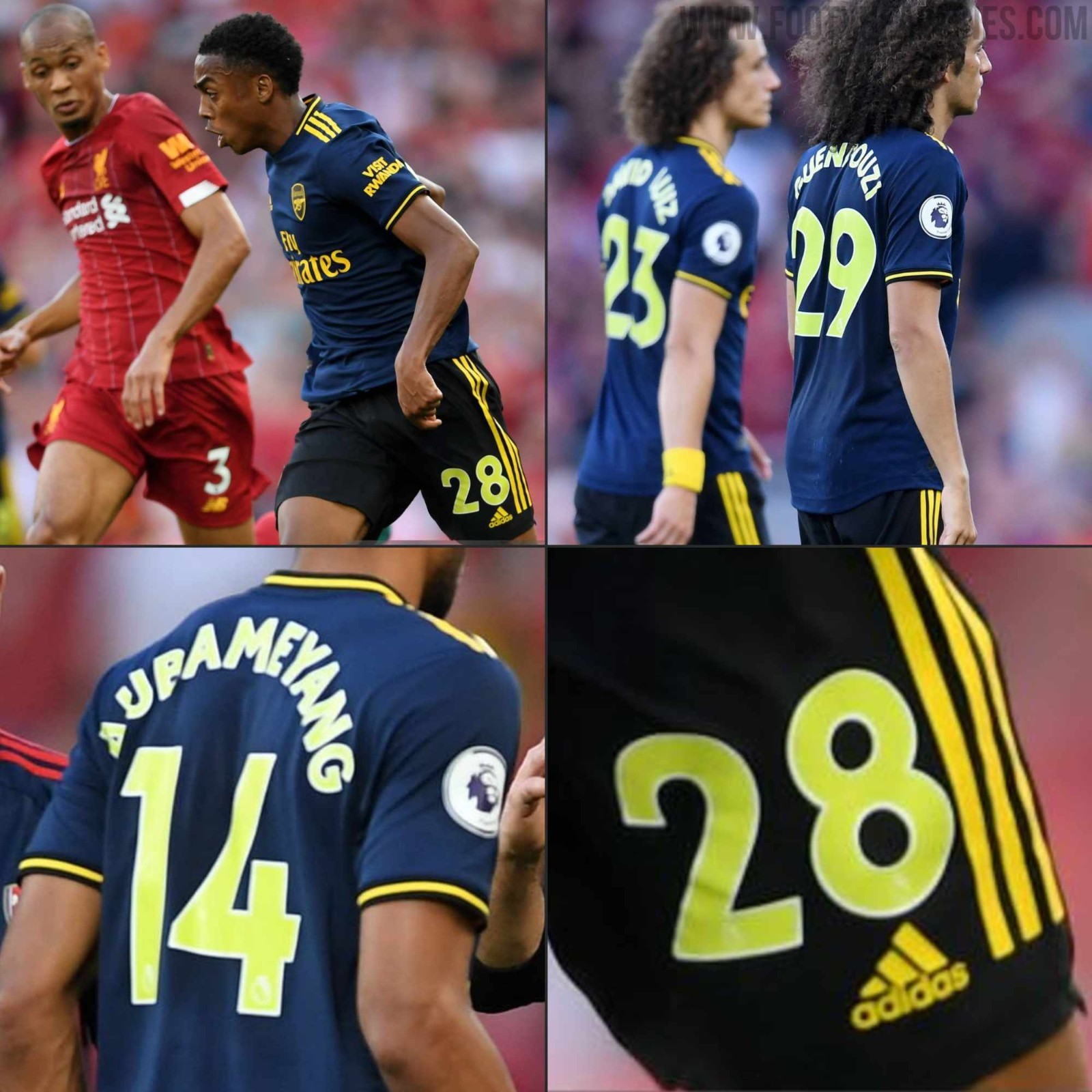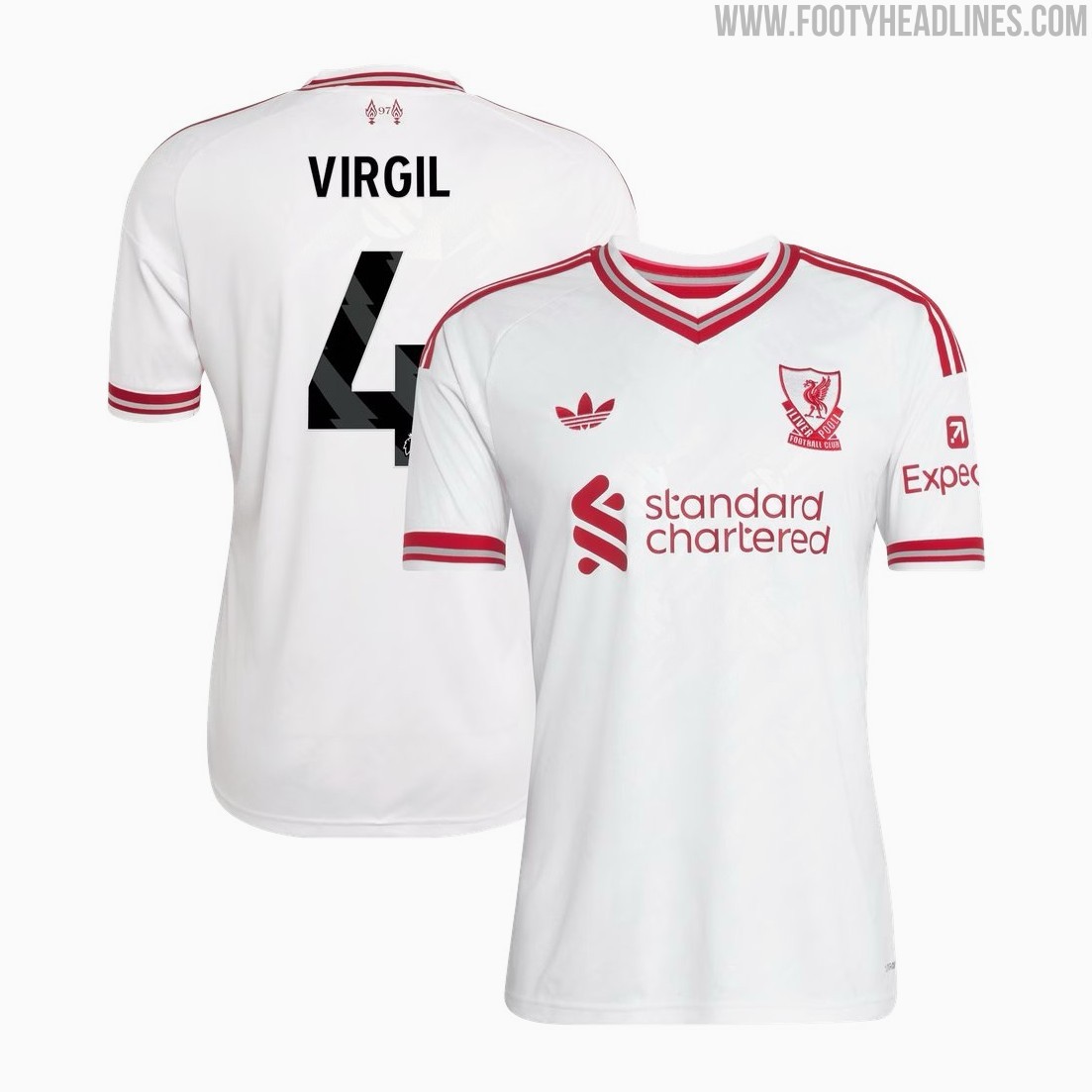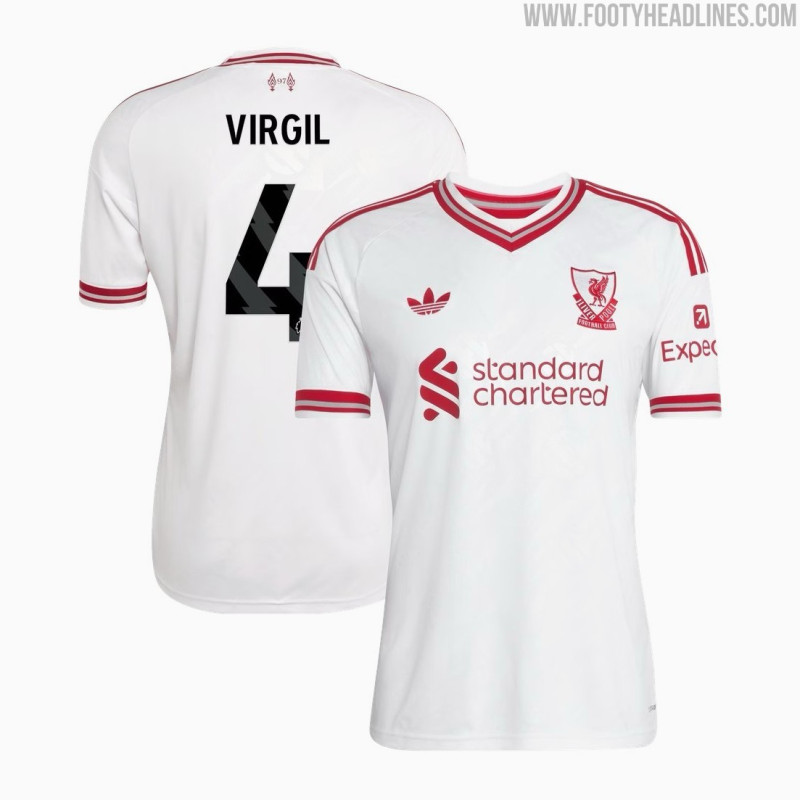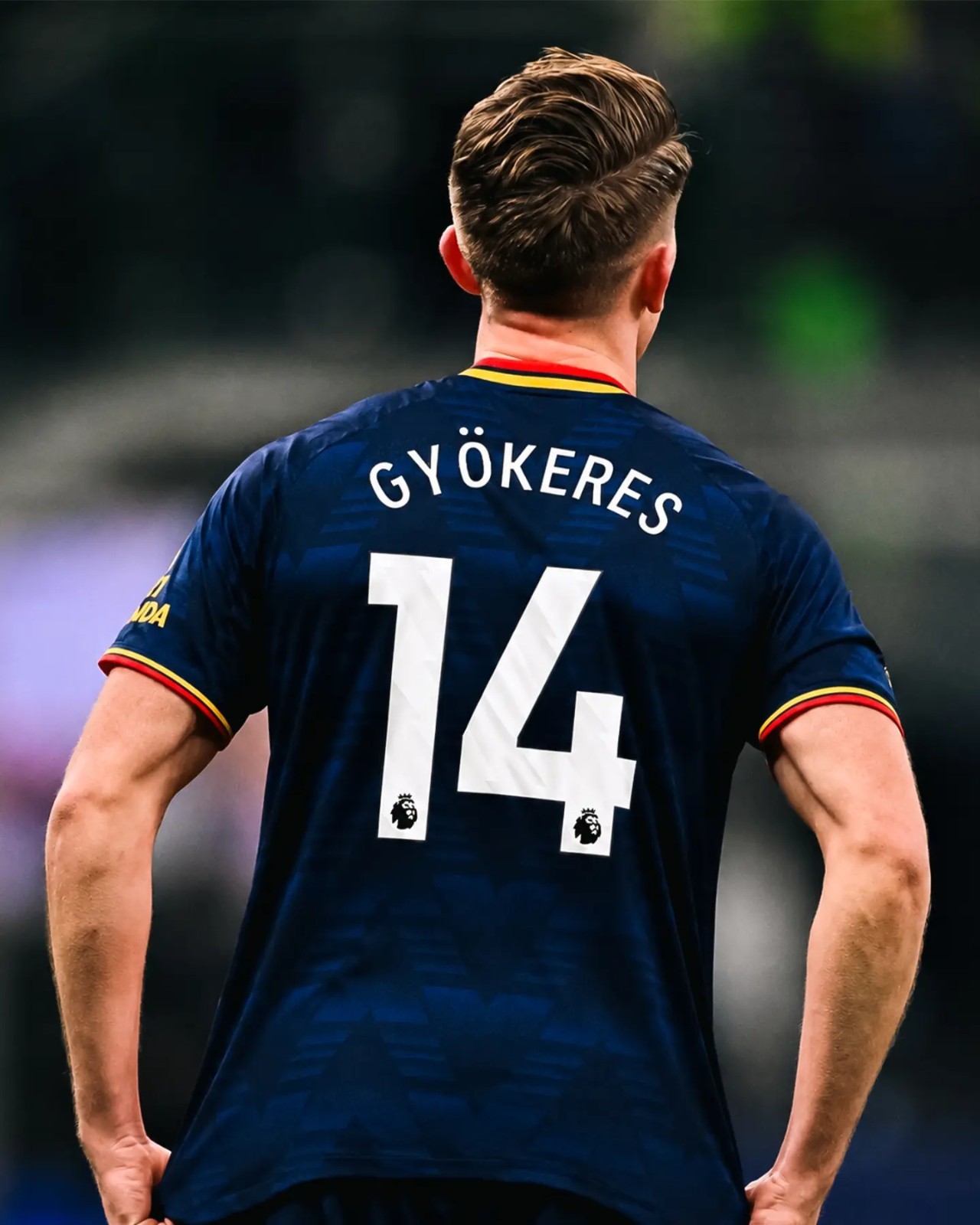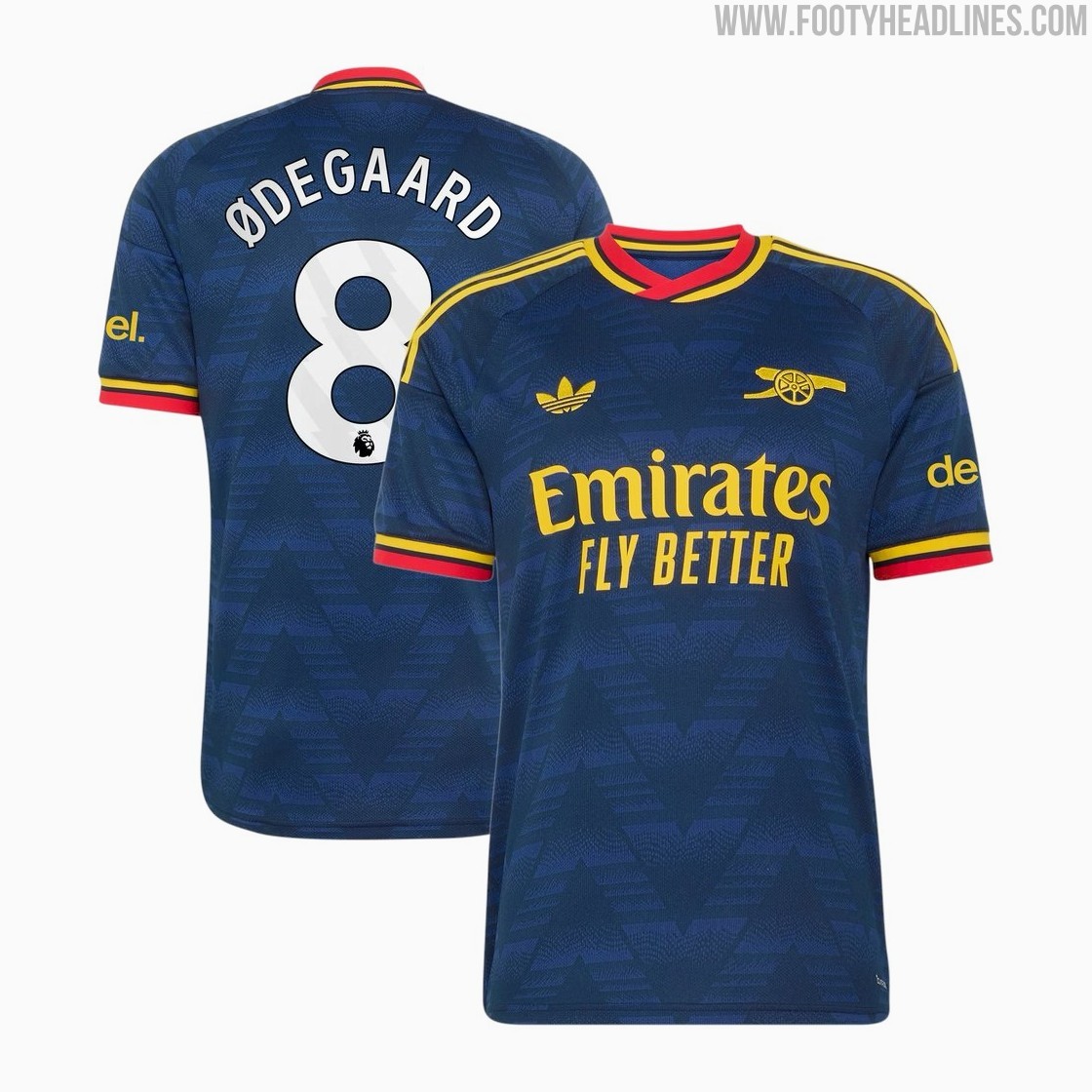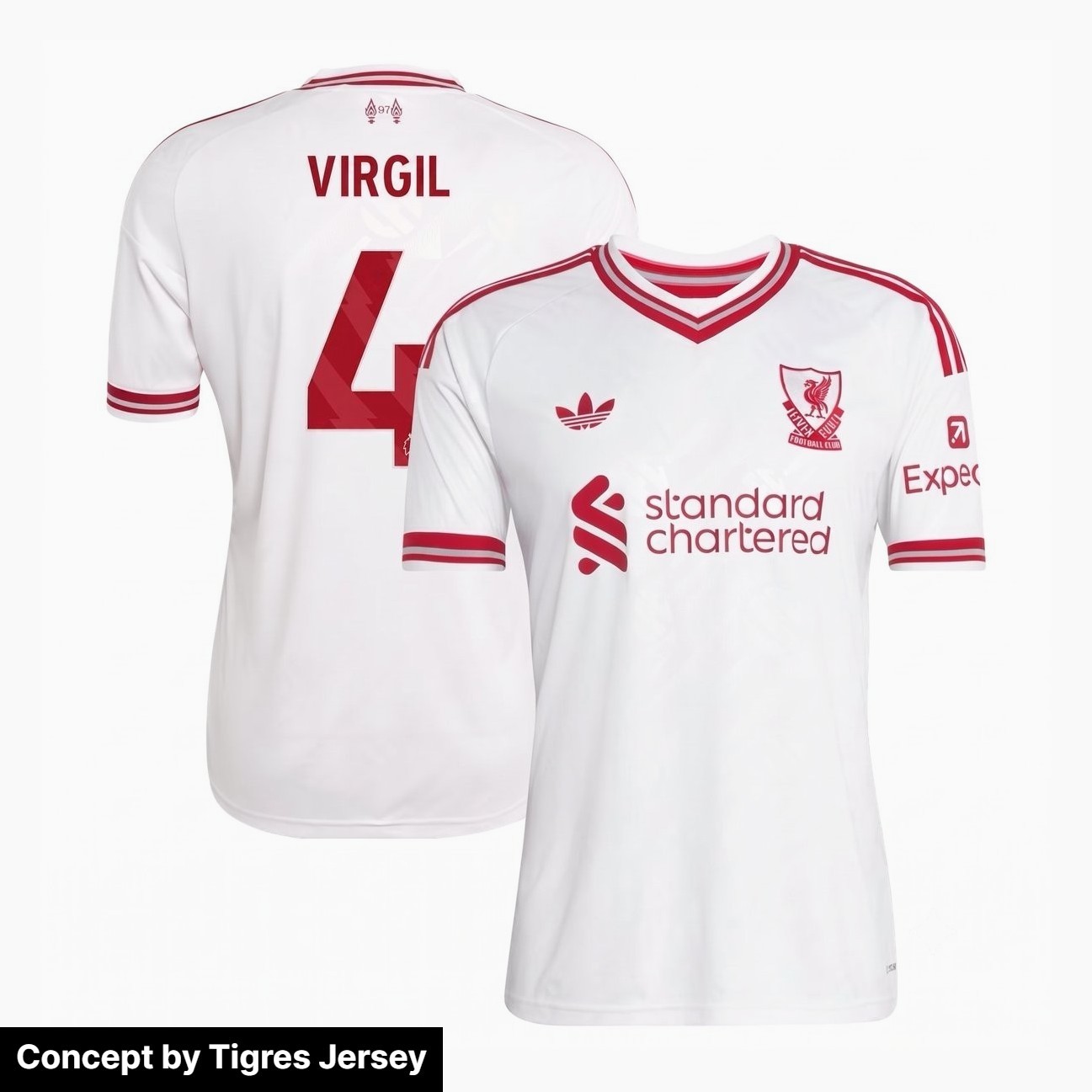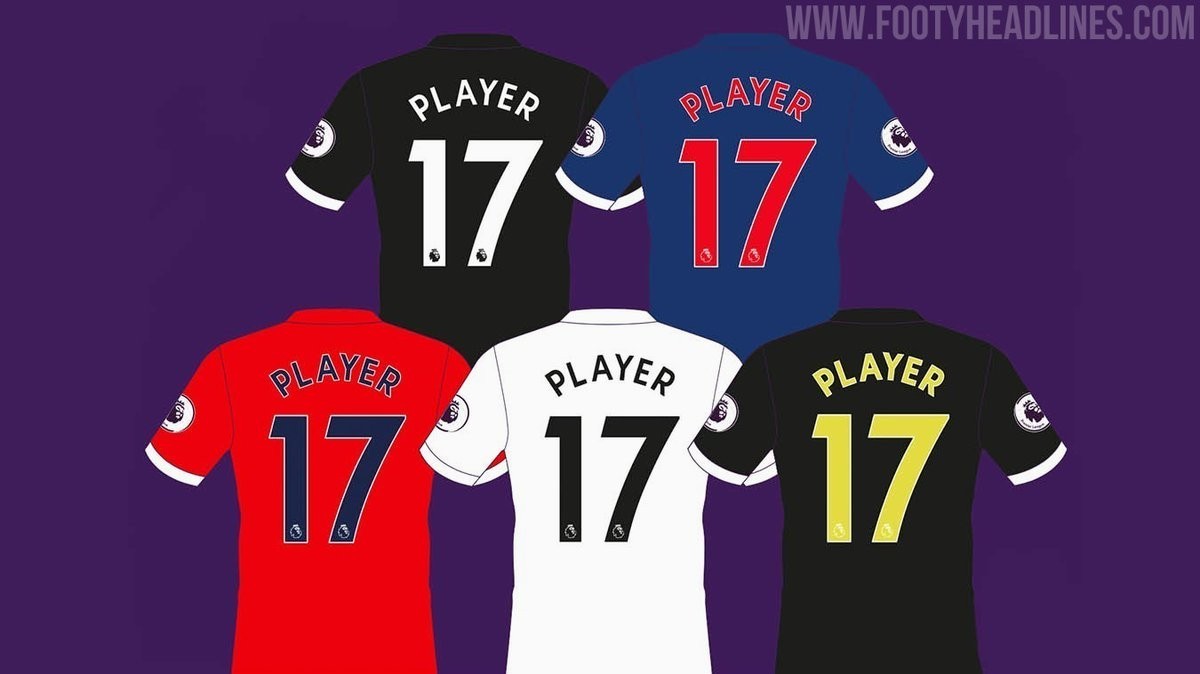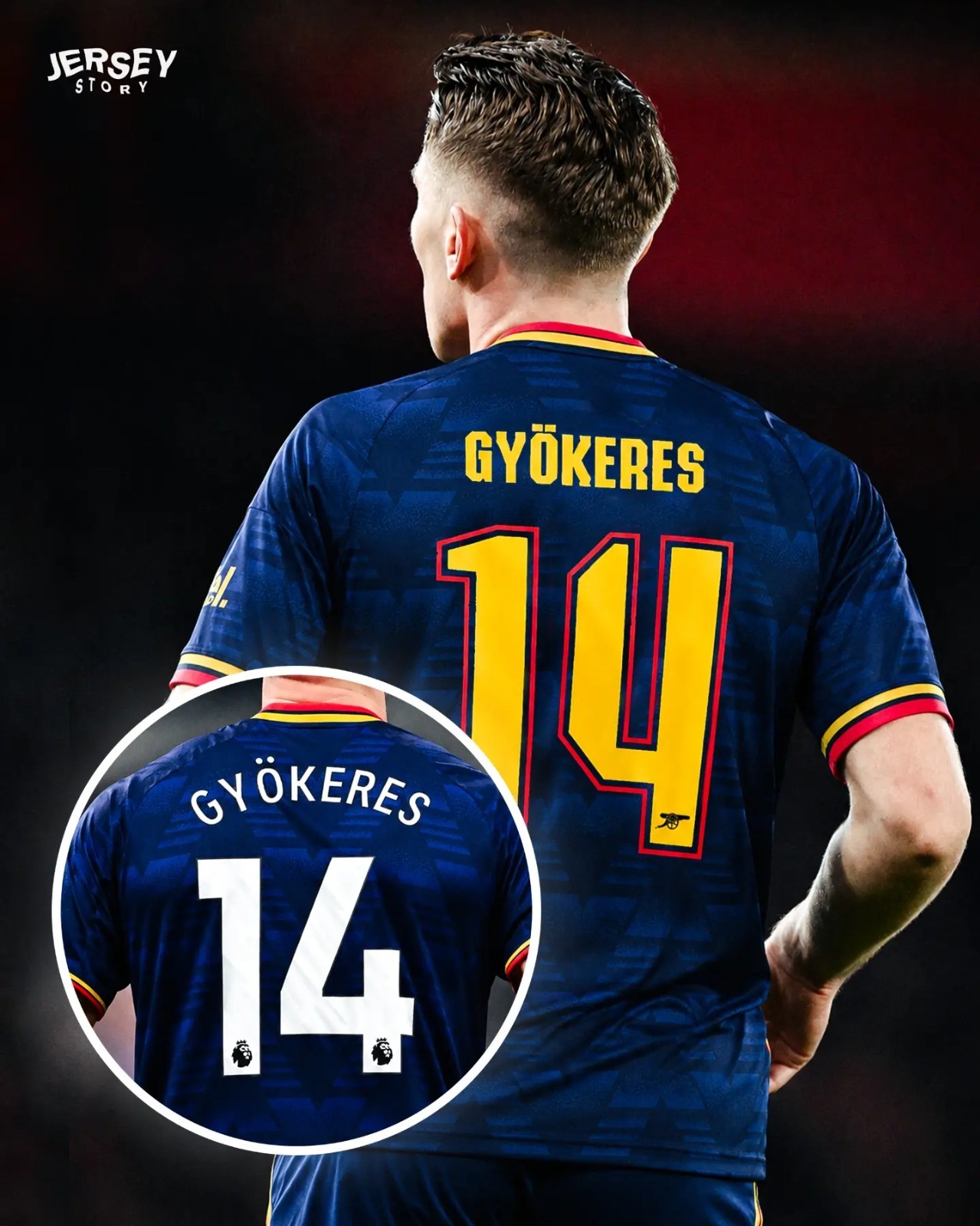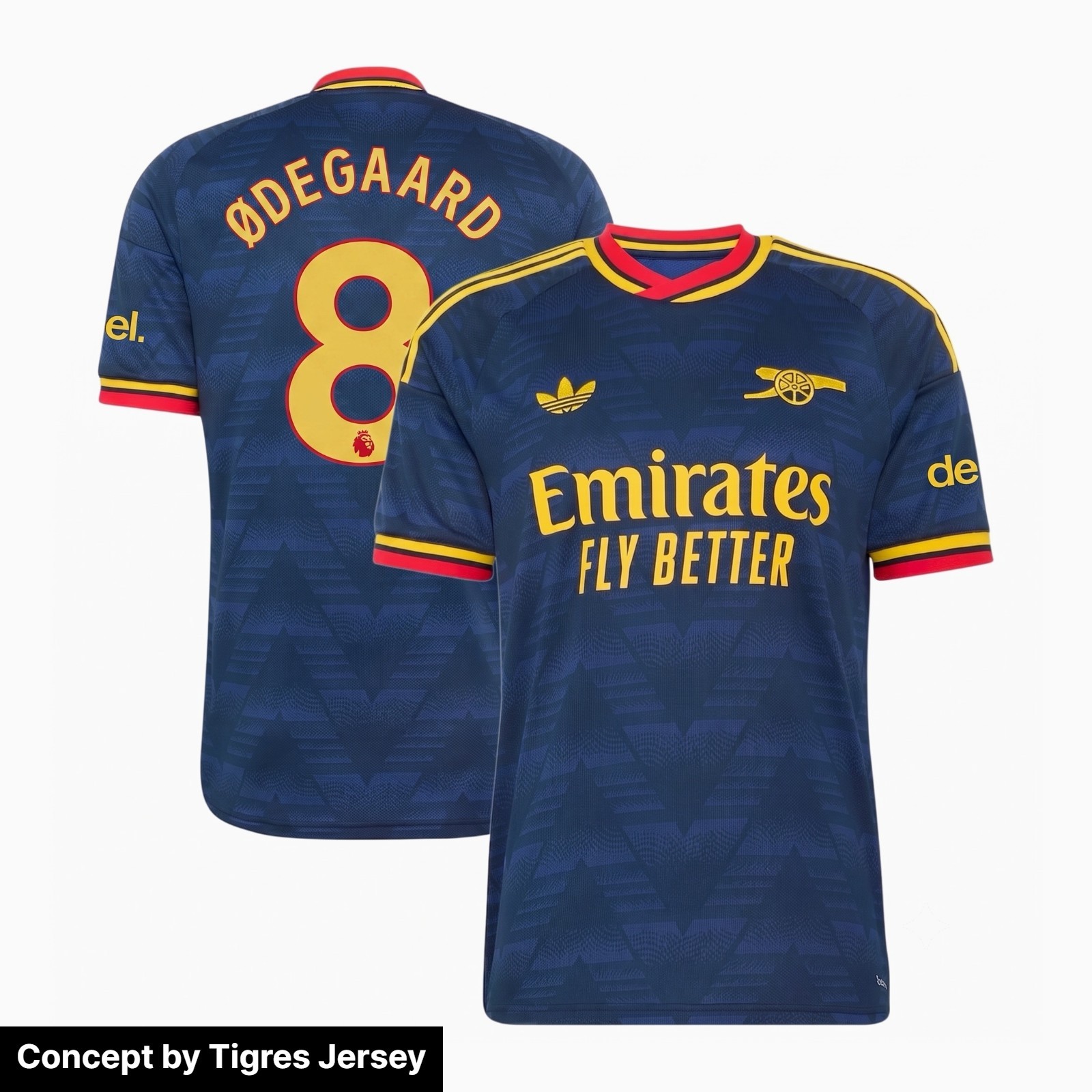
Die Premier League muss ihre unflexible Schriftart für die Trikots ändern
• Einschränkende Schriftartregeln: Die Premier League ist die restriktivste Liga im europäischen Fußball, da sie trotz einer überarbeiteten Schriftart nur fünf feste Farbvarianten für alle Trikots zulässt: Weiß, Schwarz, Rot, Marineblau und Warngelb.
• Visuelle Konflikte durch Farbauswahl: Die strikte Farbbeschränkung der Premier League führt oft zu visuellen Konflikten, da Trikothersteller individuelle Designs mit präzisen Akzentfarben erstellen, die nicht mit den vorgeschriebenen Standardfarben für Namen und Nummern harmonieren.
• Flexibilität in anderen Top-Ligen: Andere Top-Ligen wie die Serie A und La Liga erlauben Vereinen, die Farben der offiziellen Schriftart an ihre Trikotdetails anzupassen, während die Bundesliga sogar völlige kreative Freiheit bei den Schriftarten bietet, was einen flexibleren Ansatz im Trikotdesign ermöglicht.
Während standardisierte Liga-Schriftarten im europäischen Fußball mittlerweile zur gängigen Praxis geworden sind, ist die Premier League in Sachen visueller Gestaltung nach wie vor mit Abstand die restriktivste. Selbst nach der Einführung einer überarbeiteten Schriftart vor einigen Jahren hält die Liga weiterhin an einer strengen Beschränkung auf nur fünf zugelassene Farbvarianten für alle 20 Vereine fest: Weiß, Schwarz, Rot, Marineblau und Warn gelb.
Die Premier League muss ihre unflexible Schriftart für die Trikots ändern
Entwurf von Jersey Story
Unpassende Farben in der Premier League wegen nur 5 Farboptionen
Das Problem mit den Vorschriften der Premier League ist, dass sie mit dem Trikotdesign kollidieren. Trikot-Hersteller entwerfen maßgeschneiderte Trikots mit präzisen Akzentfarben wie Gold, Kastanienbraun, Creme, Mint oder sogar schlichtem Gelb. Wenn diese Trikots jedoch in Spielen der englischen Spitzenliga getragen werden, sind die Teams gezwungen, aus den fünf Standardfarben auszuwählen.
Ein Paradebeispiel dafür ist das Auswärtstrikot von Arsenal für die Saison 26/27: Dort passt sich ein farblich abgestimmter Namenszug, der in Pokalspielen verwendet wird, nahtlos an die Details des Trikots an, während die vorgeschriebene Alternative der Premier League optisch nicht zum Trikotdesign passt. In der Saison 26/27 entschied sich Arsenal für weiße Namen und Nummern – nachdem man sich in der Saison 19/20 für die leuchtend gelbe Variante entschieden hatte, die mit dem Gelb des Trikots kollidierte.
Ähnlich hat sich Liverpool für sein Premier-League-Auswärtstrikot der Saison 26/27 für Schwarz entschieden, einfach weil die rote EPL-Option einen kräftigeren Rotton hat als das von Adidas verwendete Rot.
Die mexikanischen Trikot-Experten von Tigres Jersey haben zwei Entwürfe erstellt, wie eine farblich abgestimmte Premier-League-Schriftart bei diesen Trikots aussehen würde.
Zeit, dem Beispiel anderer Ligen zu folgen
Andere Top-Ligen haben bereits gezeigt, dass Markenkonsistenz und Harmonie bei den Trikots problemlos nebeneinander bestehen können. Ligen wie die Serie A, La Liga und die MLS schreiben aus Gründen der Lesbarkeit eine einzige offizielle Schriftart vor, lassen den Vereinen aber völlige Freiheit bei der Anpassung der Schriftfarben an die jeweiligen Trikotdetails. Die Bundesliga hingegen bietet völlige kreative Freiheit, indem sie maßgeschneiderte Schriftarten für jedes Trikot zulässt.
Indem die Premier League einfach die Farbbeschränkungen lockert und gleichzeitig ihre offizielle Schriftart beibehält, könnte sie Farbkonflikte sofort lösen und das Trikotdesign in der gesamten Liga aufwerten.